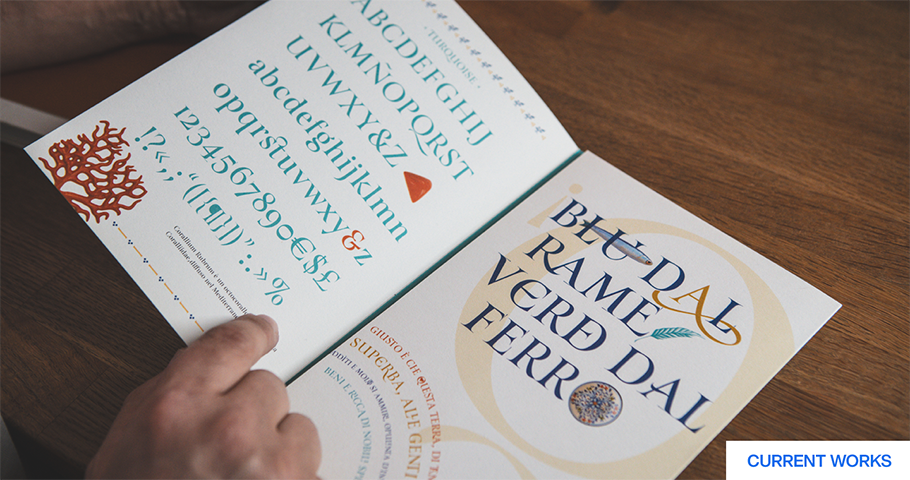
Dans le studio : Les créatifs - Giuseppe & Paco
- Giuseppe Salerno
En discutant avec Giuseppe Salerno, 43 ans, et Paco Gonzalez, 46 ans, de Resistenza (résistance) Type Foundry, basés à Turin (Italie) et à Valence (Espagne), partenaires concepteurs de police, vous aurez une leçon d'histoire du lettrage. Les deux hommes se consacrent à la production de caractères selon un processus artisanal - en créant des lettres à la main par le biais de la calligraphie - avant de numériser le site polices pour le marché contemporain..
Leur objectif : produire un travail de qualité qui dure, tout en abordant la vie quotidienne de manière décontractée. Leur mélange d'ancien et de nouveau, d'artisanat et de plaisir, alimente leur production de polices pour de grandes campagnes publicitaires et diverses marques. Parmi leurs succès, citons leur police Afrobeat Nova, qui apparaît sur la chaussure Promise Keeper de Reebok ; leur police LeKick, sur une série d'étiquettes de vin artisanal, de gin et de grappa pour le marché italien ; et leur police Mina, sur la tournée de l'album Speak Now de Taylor Swift. Nous avons discuté de leur approche du travail et de la dolce vita lors d'un récent appel Zoom.
Giuseppe Salerno (GS) : Oui, un en Italie et un en Espagne. Heureusement, notre travail nous permet de voyager facilement, car nous travaillons à distance depuis de nombreuses années. Nous passons une partie de l'année à Turin, près des montagnes, et une autre partie à Valence, près de la mer.
Paco Gonzalez (PG) : C'est un processus qui se déroule. Nous aimons manger, alors une journée dans notre studio pourrait être : nous commençons à travailler, puis l'un d'entre nous commence à cuisiner. C'est un mélange de toutes les choses que nous aimons faire, comme la typographie et la conception de lettres. Et nous avons aussi Tor, notre chien, qui est toujours là. C'est donc un travail très facile.
GS : Nous aimons profiter, sans stress. Pour nous, il est très important d'être entourés de nos livres, de nos dessins, de notre encre. J'ai constamment les mains sales, parce que je peins, j'utilise des pinceaux, j'utilise beaucoup d'outils de calligraphie. Et cela fait partie de notre style. Je dis qu'il ne faut pas s'enfermer dans un programme.
GS : La plupart du temps, nous répondons aux courriels le matin. L'après-midi, nous dessinons. C'est vers 18 heures que je travaille le mieux. Nous ne nous précipitons pas, mais nous sommes productifs. Nous avons réalisé des caractères, des étiquettes de vin et des logos pour d'autres agences. Heureusement, nous pouvons gérer ce mode de vie. Nous sommes dans le métier depuis longtemps.
GS : En 2008. Notre première publication a été Afrobeat : un site multilingue police inspiré par la musique funk africaine et nigériane du même nom. Nous aimons le patrimoine culturel, les artefacts archéologiques, les vieilles choses. Lors d'une exposition, nous avons repéré des masques de tribus africaines de la tradition nigériane, tous décorés de ces formes circulaires très optiques. C'est à partir de là que nous avons développé le lettrage [avec une forme arrondie inspirée du disco]. Puis nous nous sommes dit : pourquoi ne pas créer un alphabet mondial ?
PG : J'ai étudié le tourisme et je ne savais pas qu'il existait une activité appelée police design. Nous avons commencé à faire du graphisme ensemble. Aujourd'hui, notre travail est autodidacte.
GS : Nous avons étudié et développé nos compétences ensemble. Par ailleurs, nous avons déménagé à Berlin en 2013 pour un an, ce qui nous a permis de rencontrer pour la première fois des dessinateurs de caractères. C'est drôle, mais vrai.
PG : C'est là que nous sommes tombés sur ce projet de lettrage versus calligraphie, développé avec Martina Flor, [conceptrice de lettrage et de typographie personnalisée pour des éditeurs de premier plan tels que The Washington Post, Vanity Fair, Harper Collins, Penguin Random House, Etsy, Adobe et Cosmopolitan].
GS : Il y avait un dialogue entre nous. Nous dessinions une lettre chaque jour. Elle faisait le lettrage et moi la calligraphie, en suivant une certaine qualité. Voici le site web qui présente notre travail : https://www.letteringvscalligraphy.com/
À cette époque, en Europe, il y avait une renaissance du lettrage et de la calligraphie. Instagram a eu peu d'influence. Tout le monde se disait : pourquoi, soudainement, le travail fait à la main est-il important ?
MF : Pourquoi ?
GS : Il y a cette impulsion de ramener ce que nos ancêtres ont fait - un respect pour ce qui a été fait avant. Par exemple, nous aimons voyager dans le sud de l'Italie, où l'influence des inscriptions romaines [sur les temples païens, sur les reliques] est très forte. Nous avons l'habitude d'être entourés de belles lettres qui ont résisté au temps. Il dure. C'est notre concept de Resistenza.
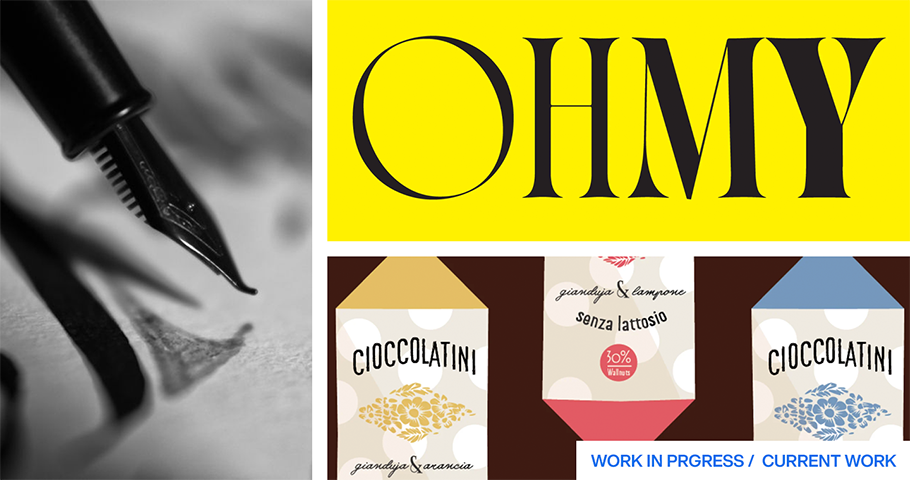
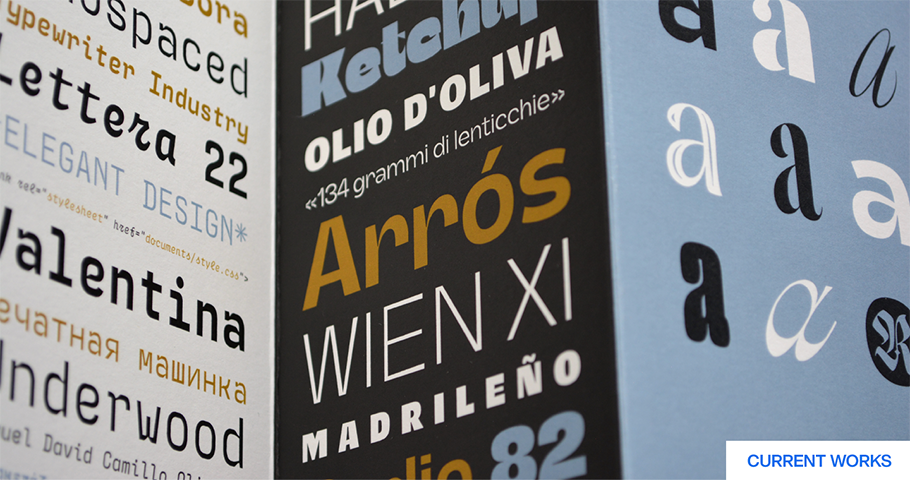
MF : Sur quoi travaillez-vous actuellement ?
GS : Sortir notre premier livre sur les polices de caractères. Il est encore en cours de réalisation : cent cinquante pages ! Nous avons les premiers exemplaires et nous espérons qu'il sera prêt en septembre. Il s'agit de toutes les années de notre polices reproduites dans un catalogue.